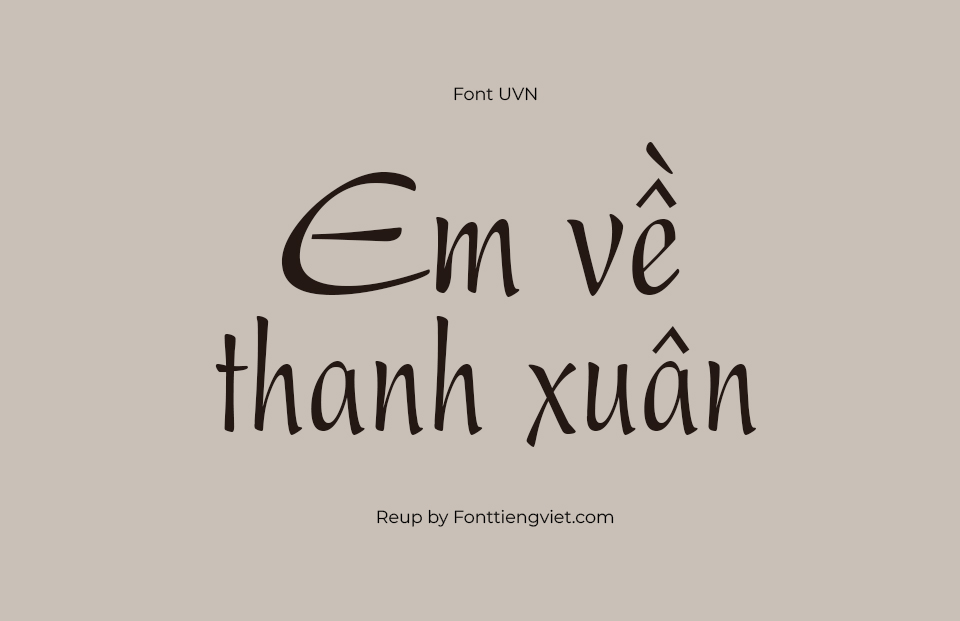
Font Việt Hóa UVN Bay Buom Hep
Font Việt Hóa UVN Bay Buom Hep – Bộ Font Chữ Nghệ Thuật Cho Học Đường
Giới thiệu về Font Việt Hóa UVN Bay Buom Hep
Trong thế giới thiết kế đồ họa dành cho giáo dục, việc tìm kiếm một bộ Font Miễn Phí có phong cách thanh mảnh và tinh tế luôn là ưu tiên hàng đầu. Font Việt Hóa UVN Bay Buom Hep là một trong những lựa chọn tuyệt vời nhất thuộc bộ sưu tập UVN nổi tiếng. Với thiết kế đặc trưng là các nét chữ cao, hẹp và bay bổng, bộ font này mang lại cảm giác nhẹ nhàng như cánh bướm, giúp các văn bản tiếng Việt trở nên nghệ thuật và thu hút hơn bao giờ hết.
Đặc điểm nổi bật của font chữ
Font Việt Hóa UVN Bay Buom Hep sở hữu cấu trúc chữ nén (condensed), giúp tiết kiệm diện tích nhưng vẫn giữ được sự rõ ràng. Các dấu câu tiếng Việt được tinh chỉnh tỉ mỉ, không bị đè nét hay lỗi hiển thị, rất phù hợp cho học sinh và giáo viên khi soạn thảo giáo án hoặc làm báo tường. Đây là bộ font lý tưởng để trình bày các tiêu đề bài thơ, thiệp mời hoặc các đoạn trích dẫn ý nghĩa trong môi trường học đường.
Ứng dụng thực tế của Font Việt Hóa UVN Bay Buom Hep
Nhờ vẻ ngoài thanh thoát, Font Việt Hóa UVN Bay Buom Hep thường được sử dụng trong các dự án thiết kế slide bài giảng điện tử hoặc làm tựa đề cho các tờ báo nhi đồng. Khi kết hợp với những tông màu pastel, font chữ này tạo nên một không gian học tập đầy sáng tạo và thân thiện. Ngoài ra, tính năng việt hóa hoàn chỉnh giúp người dùng dễ dàng gõ văn bản chuẩn bảng mã Unicode mà không gặp bất kỳ trở ngại nào về kỹ thuật.
Lưu ý khi sử dụng trong thiết kế
Vì là kiểu chữ dạng hẹp, bạn nên sử dụng Font Việt Hóa UVN Bay Buom Hep cho các đoạn văn ngắn hoặc tiêu đề chính để đạt hiệu quả thị giác tốt nhất. Tránh dùng cho các văn bản quá dài vì có thể gây mỏi mắt cho người đọc. Hãy tận dụng tối đa sự mềm mại của các đường cong để làm nổi bật thông điệp mà bạn muốn truyền tải.
Kết luận về bộ font độc đáo